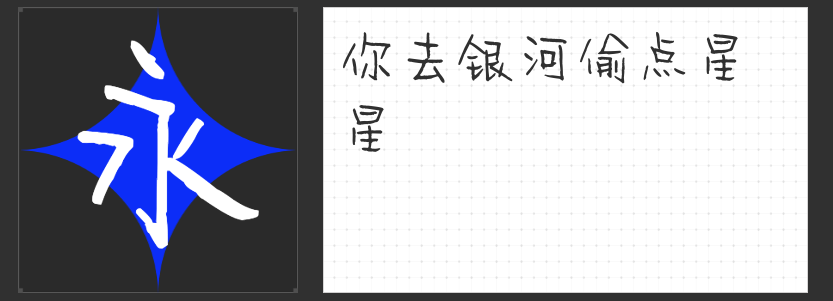
萌~动~字~心 四款字体唤醒设计元气
在追求视觉亲和力的设计领域,可爱字体就像甜品店里的马卡龙——用糖分激活多巴胺,让观者在第一时间卸下心防。今次精选四款风格迥异的可爱字体,它们或憨态可掬,或灵动俏皮,为设计注入治愈系能量。
一、喵字文案体
这款字体深谙"可爱"的高级形态,将传统书法的气韵化作绵软的猫爪肉垫。笔画转折处圆润如满月,提按之间暗藏呼吸感,恰似猫咪轻触宣纸的优雅。用于品牌故事文案时,能让"匠心"二字生出毛茸茸的暖意;落在公益海报上,则使"关爱"的呼吁化作绕指柔。
二、MyFont凌渡未卜简
当卡通基因注入字体DNA,便诞生了这朵手绘风格的可爱云朵。笔画如孩童蜡笔画的颤抖线条,却在中宫收紧的设计中保持视觉平衡。特别适合儿童绘本内文,字母"o"化作摇头晃脑的小熊,标点变成跳舞的兔子,让阅读成为游乐园探险。
三、励字憨憨简
这款字体自带"天然呆"属性,每个笔画都像被圆规亲吻过。横竖弯钩饱满如糯米团子,点画俏皮如跳跃的糖豆。用于零食包装设计时,"咔嚓"二字会溢出薯片脆响;印在文创周边上,能让博物馆文创摆脱严肃面孔。
四、喵字动漫体
在二次元世界与现实维度间,这款字体架起律动的桥梁。笔画如动画分镜线稿,排版带着赛璐璐时代的错位萌感。特别适合游戏Loading界面,文字仿佛随着进度条轻颤;落在漫画扉页,则让对话框生出镜头语言。
四款字体如同四枚情绪糖果,表达可爱方式虽然不同,但都超级可爱!它们用笔画搭建起情感坐标系,让设计在可爱维度自由延展。